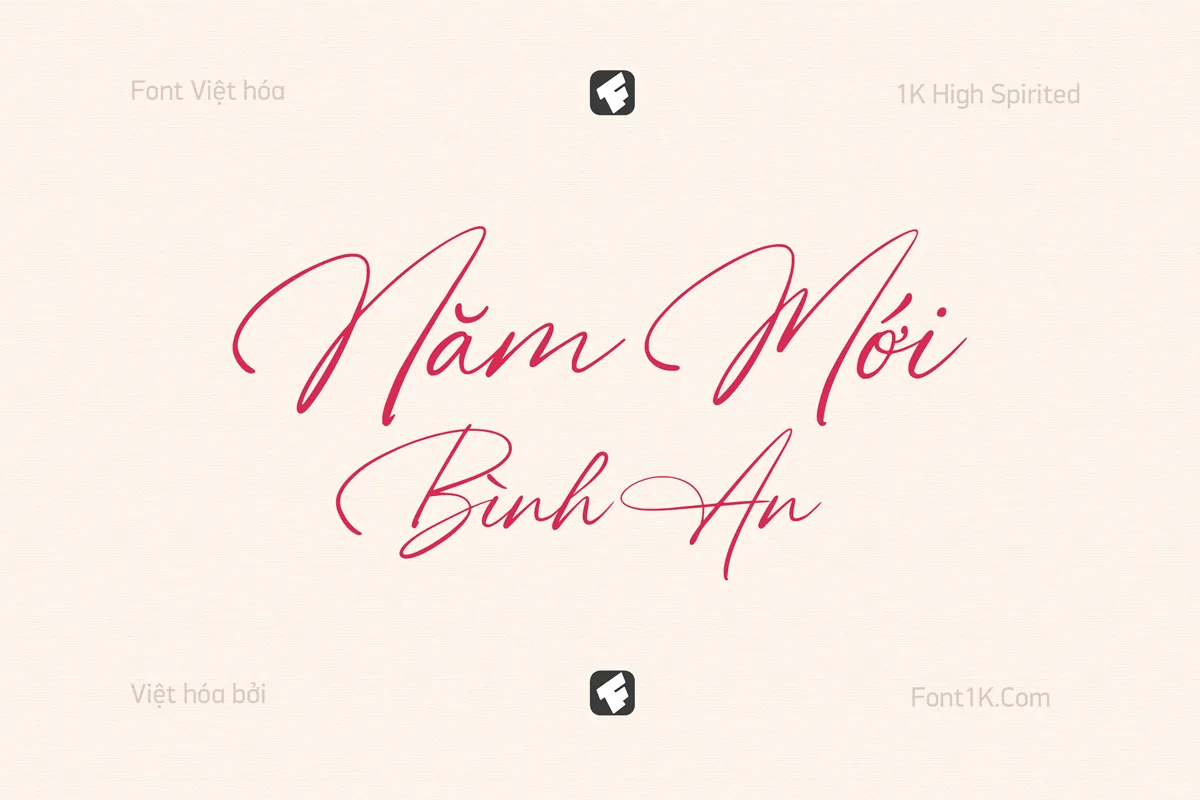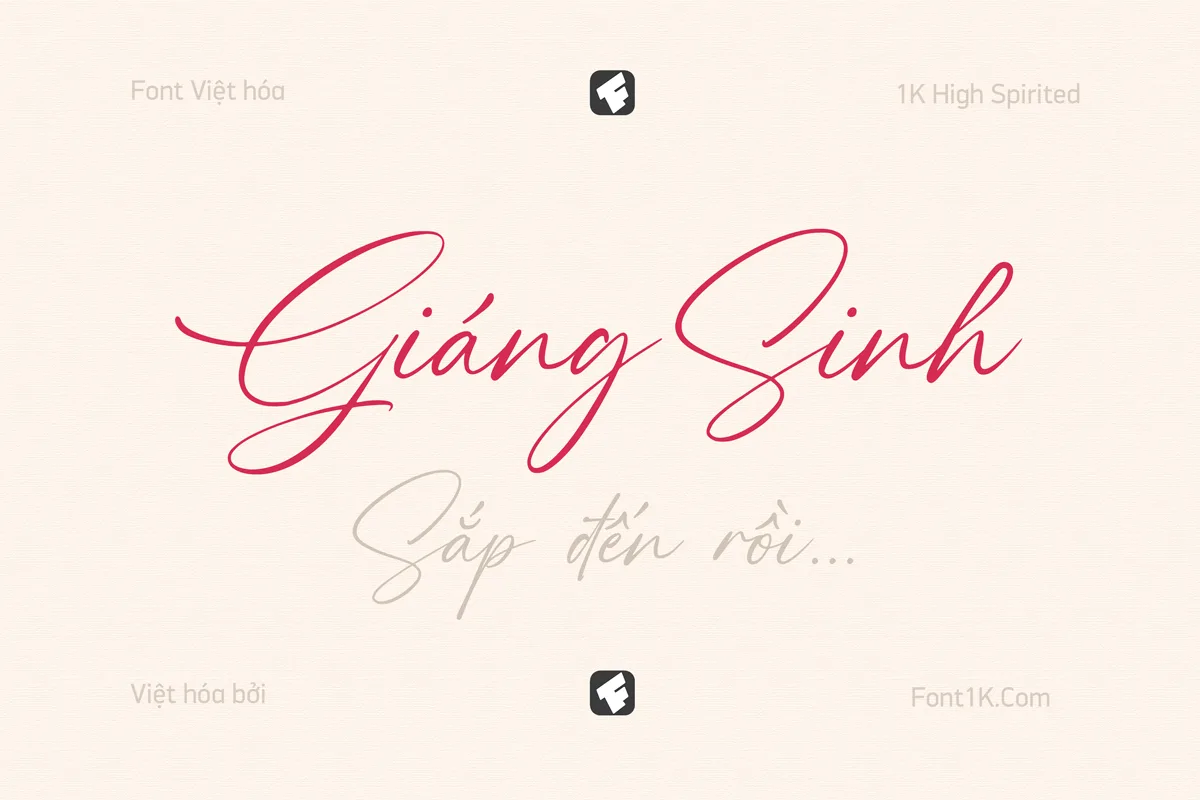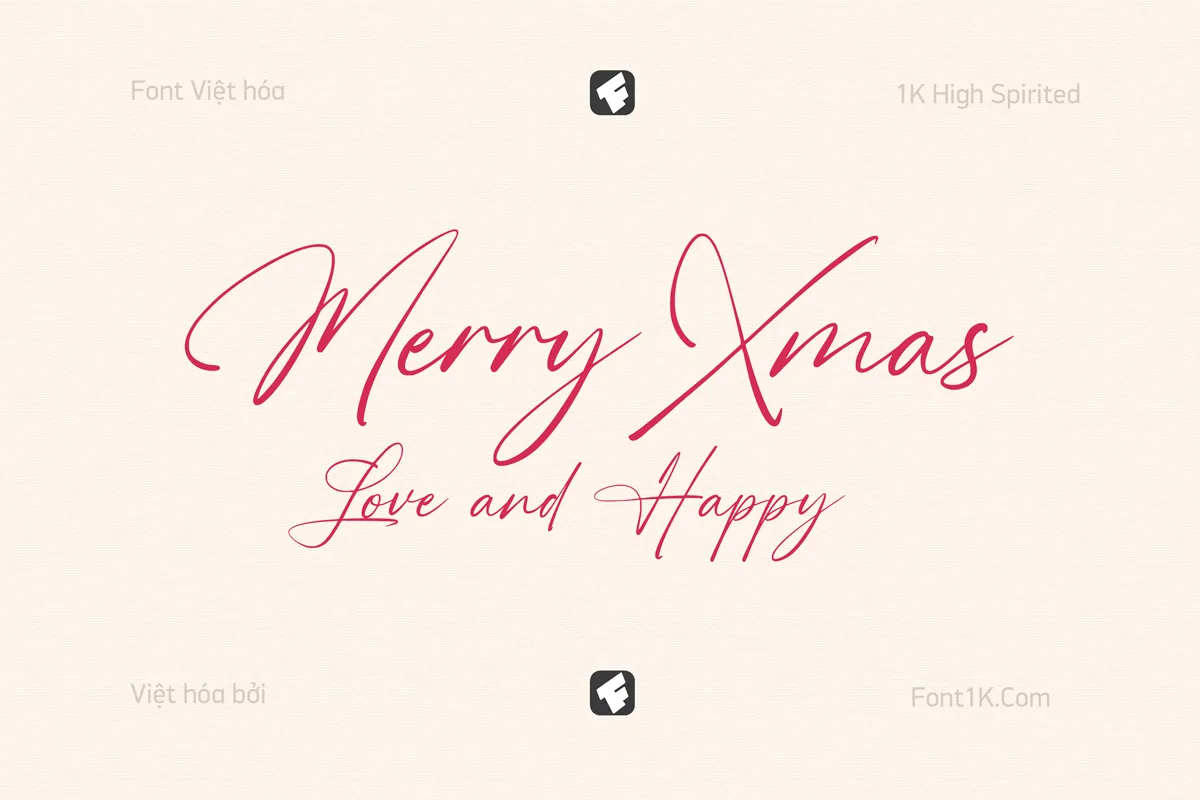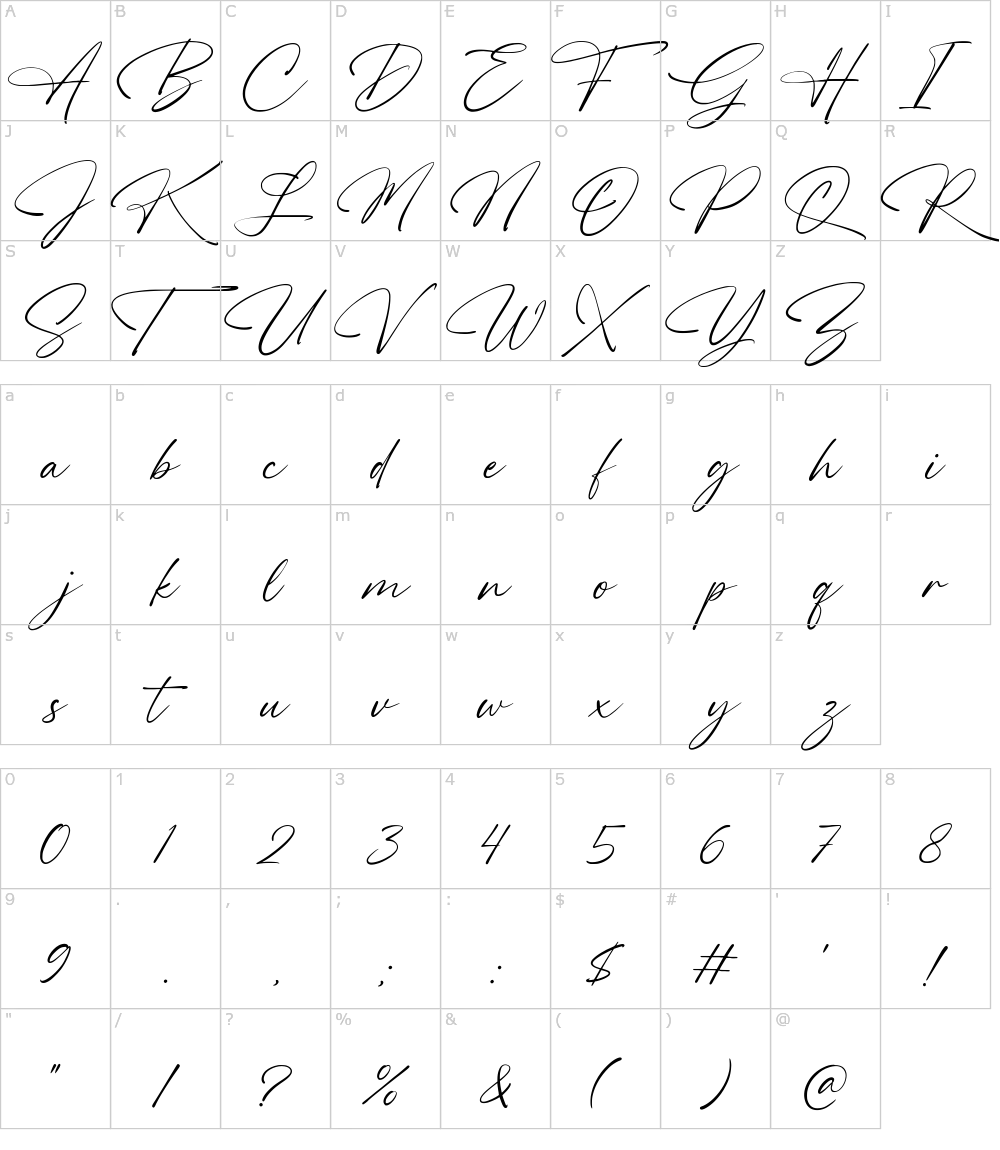
Font chữ viết tay việt hóa 1K High Spirited với phong cách tự nhiên
Font chữ viết tay việt hóa 1K High Spirited với phong cách tự nhiên, mềm mại và uyển chuyển. Font này mang lại cảm giác nhẹ nhàng, thân thiện, nhưng không kém phần tinh tế, giúp bạn dễ dàng áp dụng trong nhiều dự án thiết kế khác từ đơn giản đến chuyên nghiệp!
Font chữ viết tay 1K High Spirited
Font chữ viết tay 1k high spirited
Được thiết kế bởi Octotype và Việt hóa bởi Font1K, 1K High Spirited là một font chữ viết tay chất lượng cao, đáp ứng mọi yêu cầu của các nhà thiết kế. Với sự kết hợp hoàn hảo giữa tính thẩm mỹ và tính ứng dụng, font chữ này sẽ giúp bạn tạo ra những sản phẩm thiết kế chuyên nghiệp, ấn tượng.
• Ưu điểm:
• Phong cách đa dạng, phù hợp nhiều loại hình thiết kế.
• Hỗ trợ đầy đủ tiếng Việt, đảm bảo tính chuyên nghiệp.
Hình ảnh demo font 1K High Spirited việt hóa
Dưới đây là hình ảnh demo sử dụng font 1K High Spirited làm text chính trong thiết kế.
Font chữ viết tay 1k high spirited
Ký tự trong font 1k high spirited
Ký tự trong font 1K High Spirited